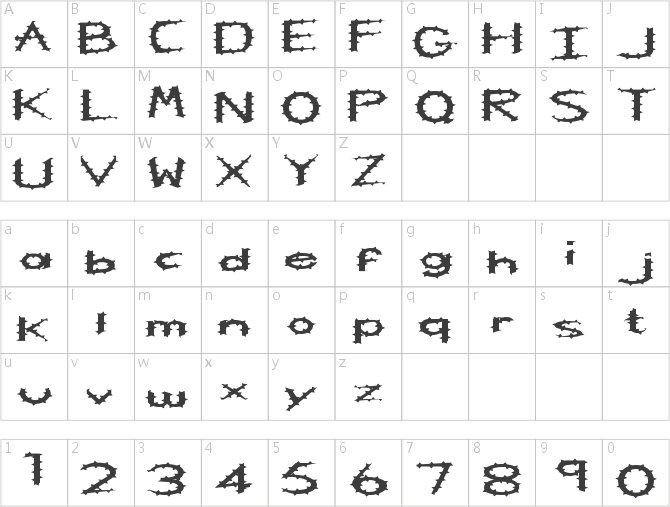
FZ HAND 5 SPIKED EX
FZ HAND 5 SPIKED EX字體字庫(kù)是一款讓人賞心悅目、百看不厭的英文字體,適合各類(lèi)廣告和產(chǎn)品包裝設(shè)計(jì)應(yīng)用,字體大小0.07MB,格式為ttf字體,上傳用戶(hù)是g05662,作者/版權(quán)方為未知